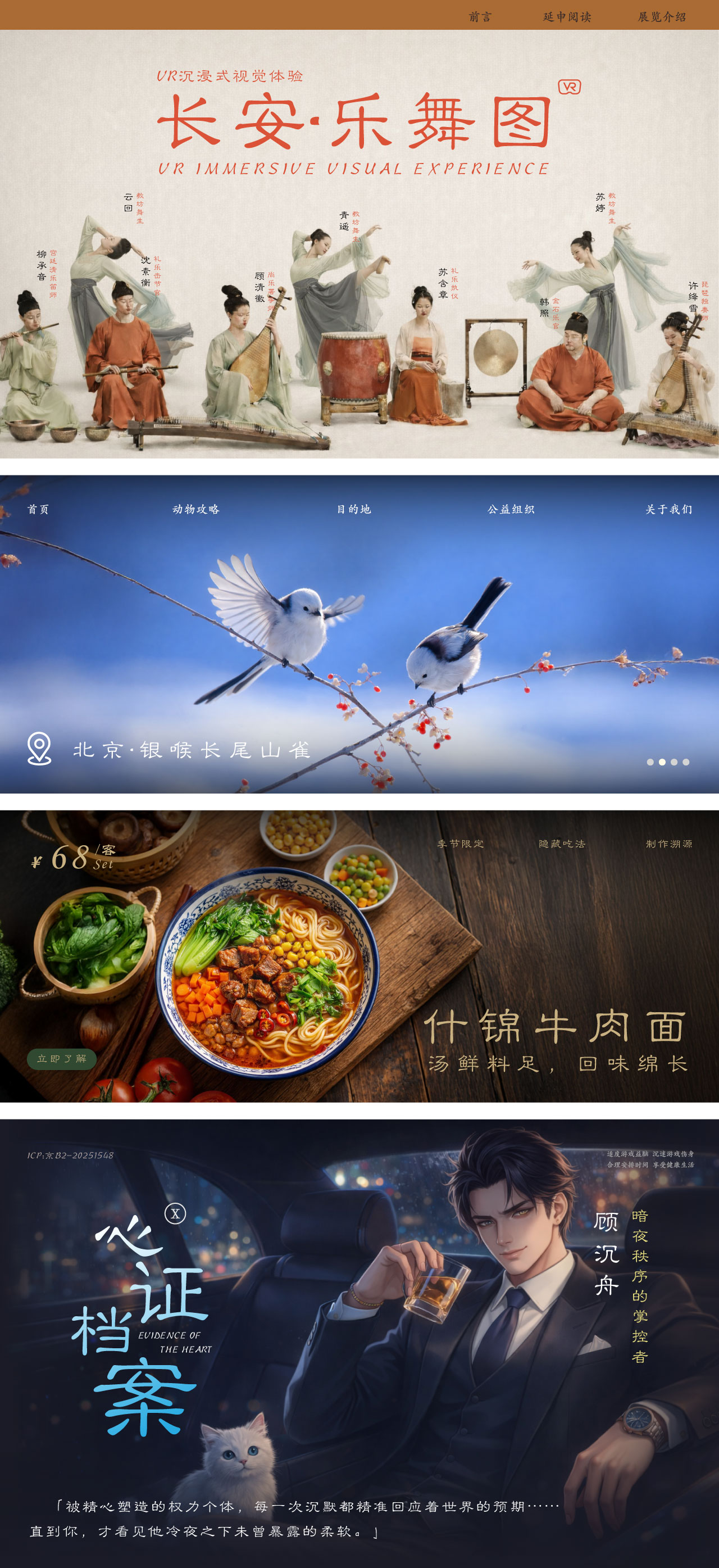
华文隶变 / STLibian / Regular
华文隶变
在有限的空间进行无限分割
华文隶变 / STLibian
Regular
设计师:
常州华文
字体介绍:
华文隶变起笔收笔严格遵循了“上则抑,下则扬”的起伏原则,横划一波三折,飘逸舒展,竖划内敛遒劲,古朴庄重,整体收放有致、黑白相应、清晰明快、栩栩如生。